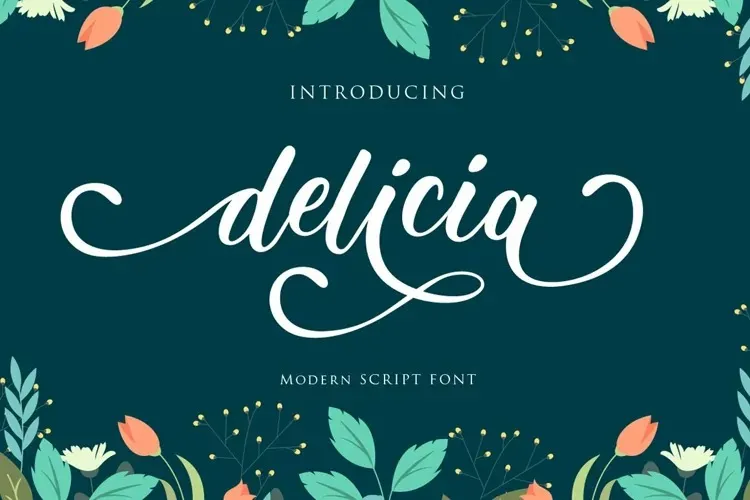
Delicia Font é uma elegante fuçna script que surge com simples sutilezas, criada pelo produtor de materiais fanastudio. Suave e prático, esta fuçna adere à sua arte e torna-a exuberante. É perfeita para design de anúncios de casamento, cartas de agradecimento, eventos de casamento, cartões de boas-vindas, logotipos e muito mais — Delicia é uma escolha sólida para qualquer projeto que necessite de um estilo personalizado. Sua presença poética vai tornar seus projetos ainda mais belos e únicos. O design de fanastudio foi cuidadosamente criado para abraçar a diversidade do design gráfico, tornando-se uma fonte versátil para qualquer designer que procura um toque delicado na sua arte.